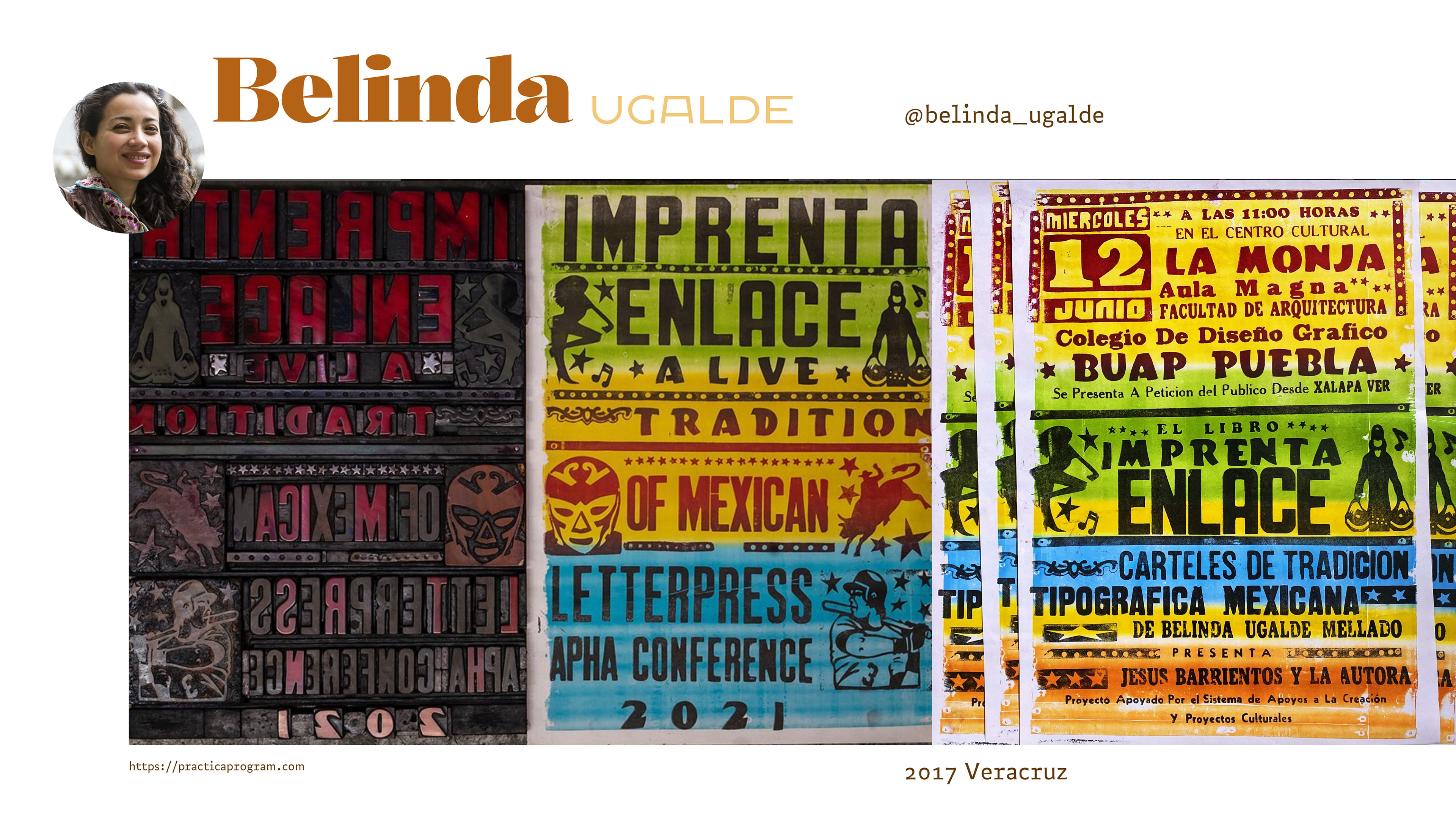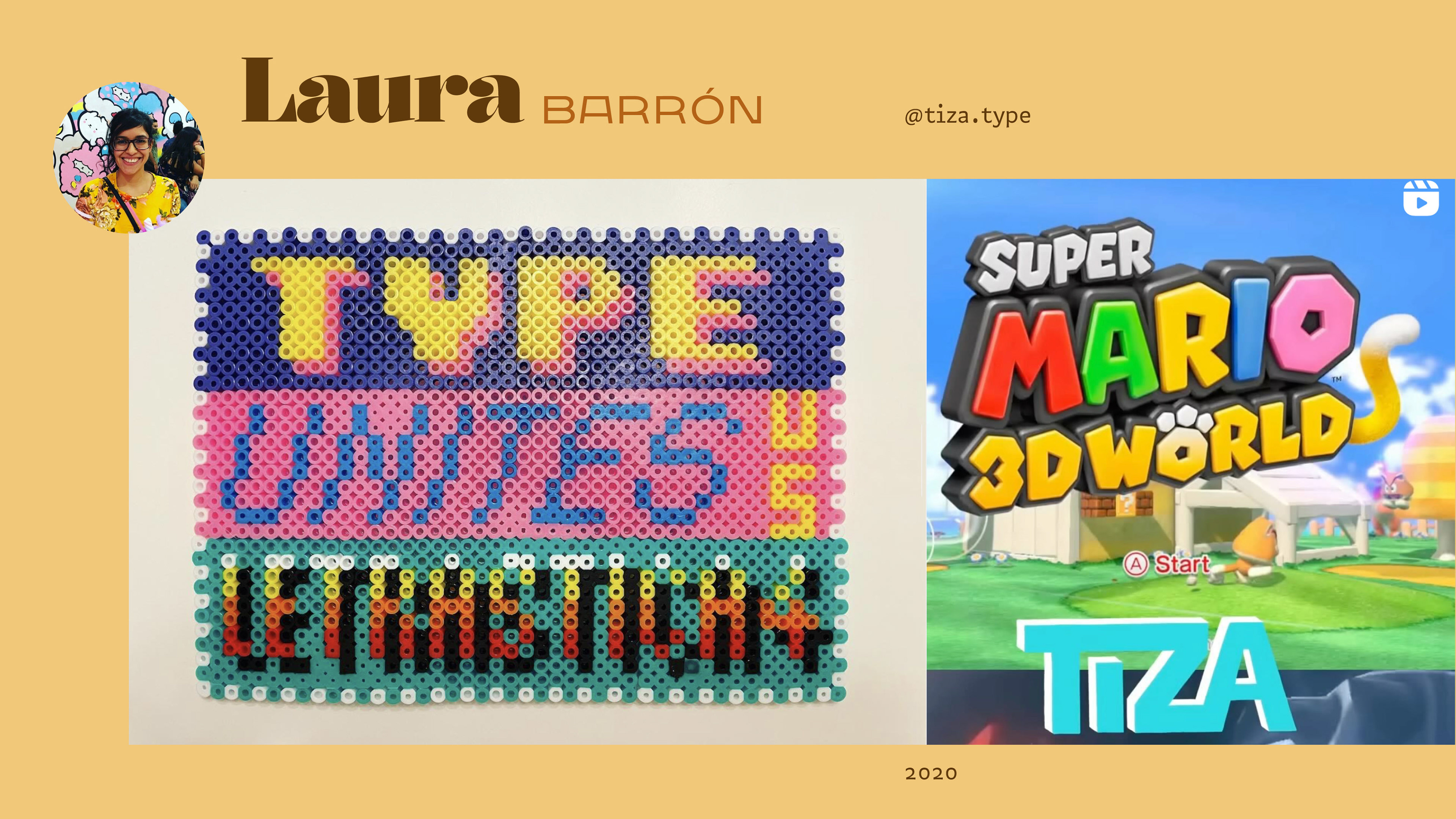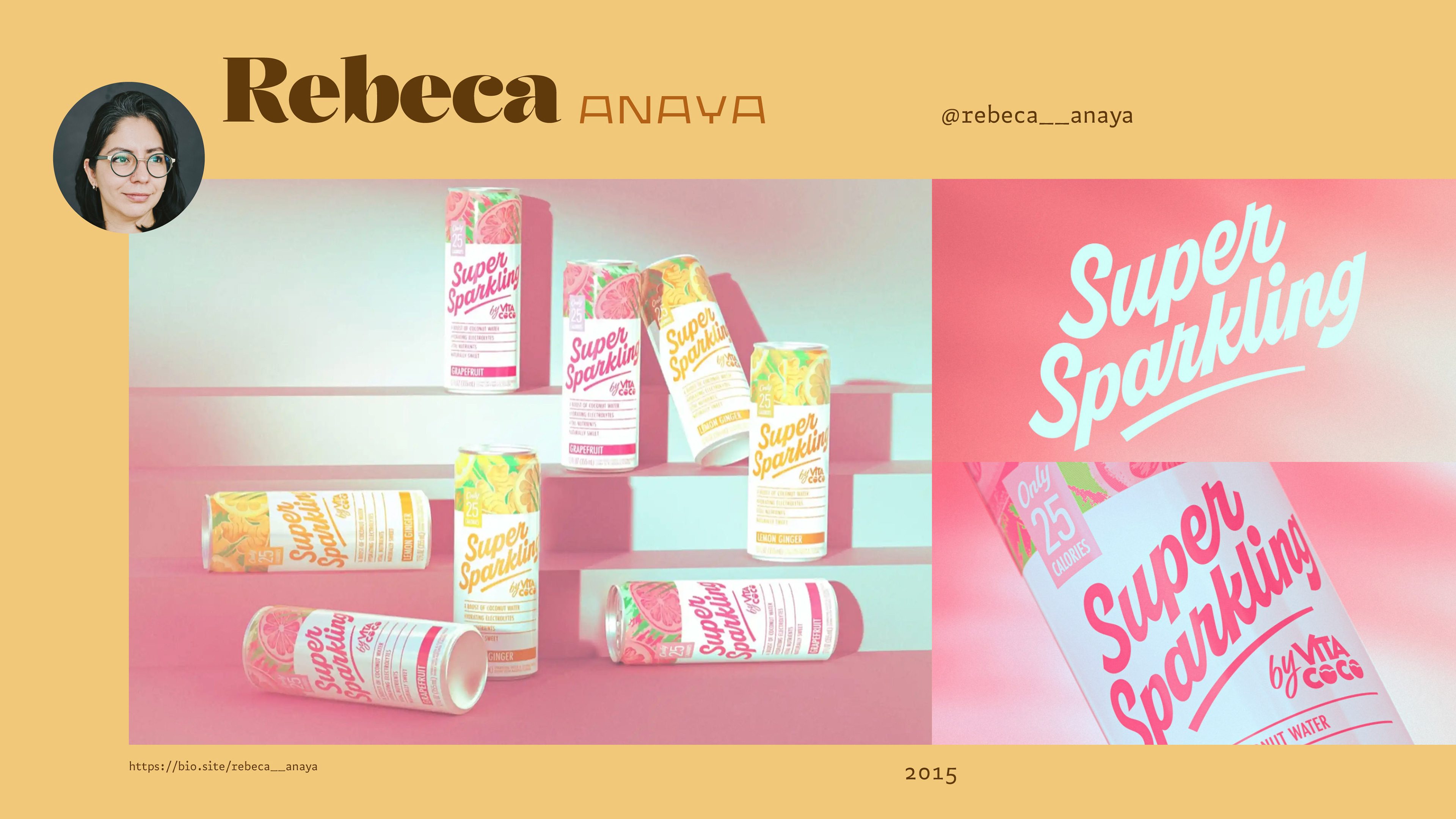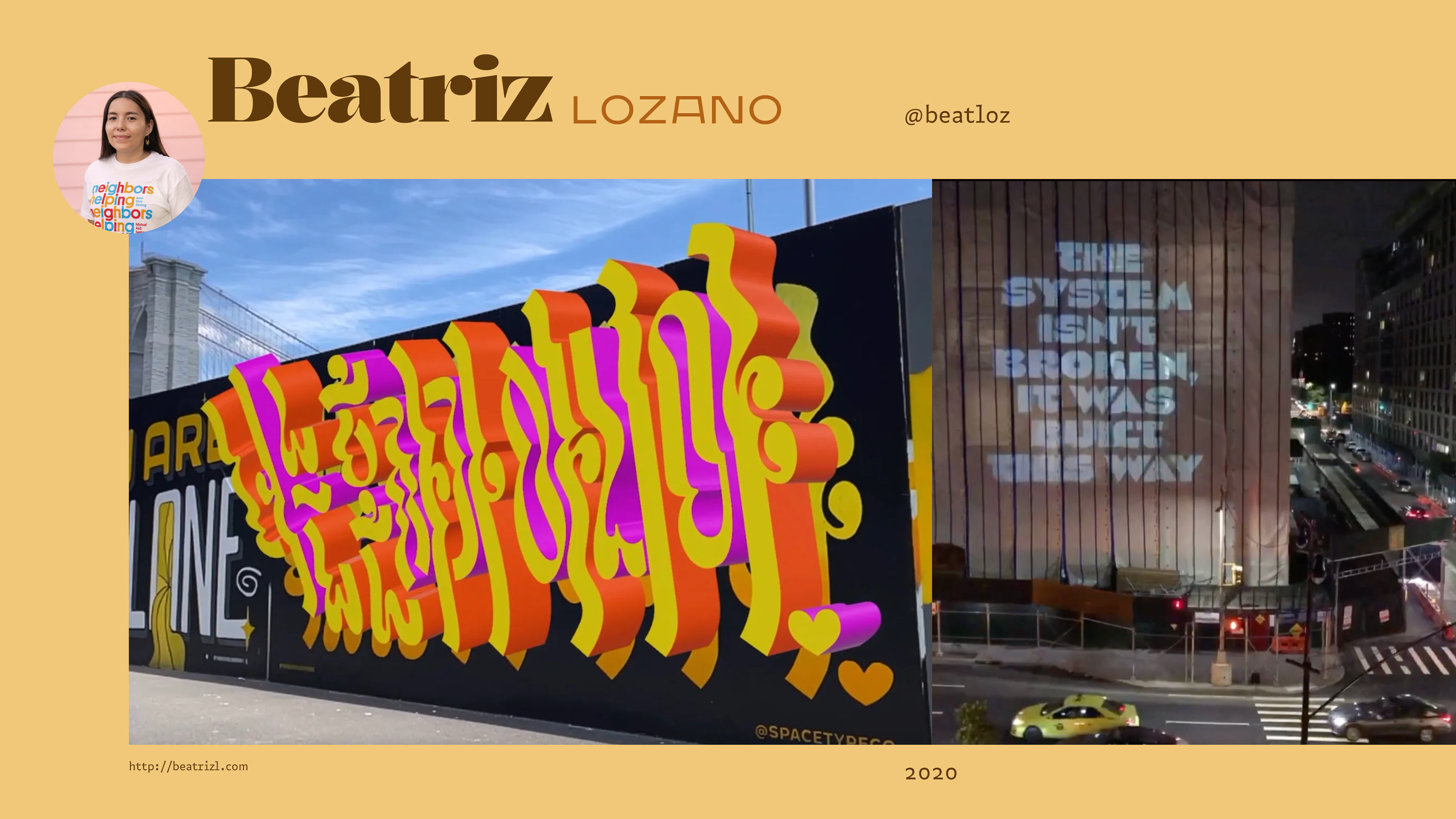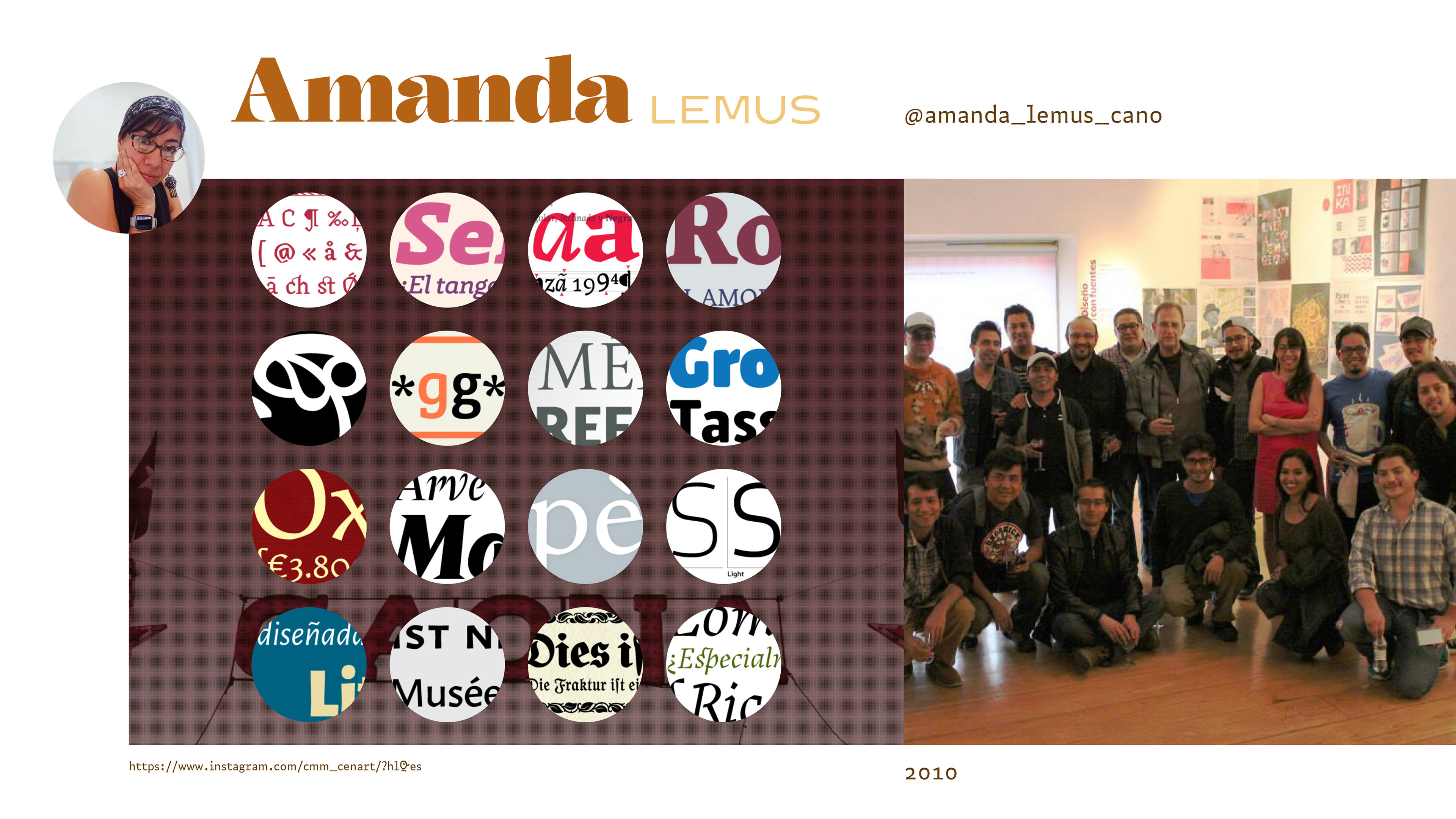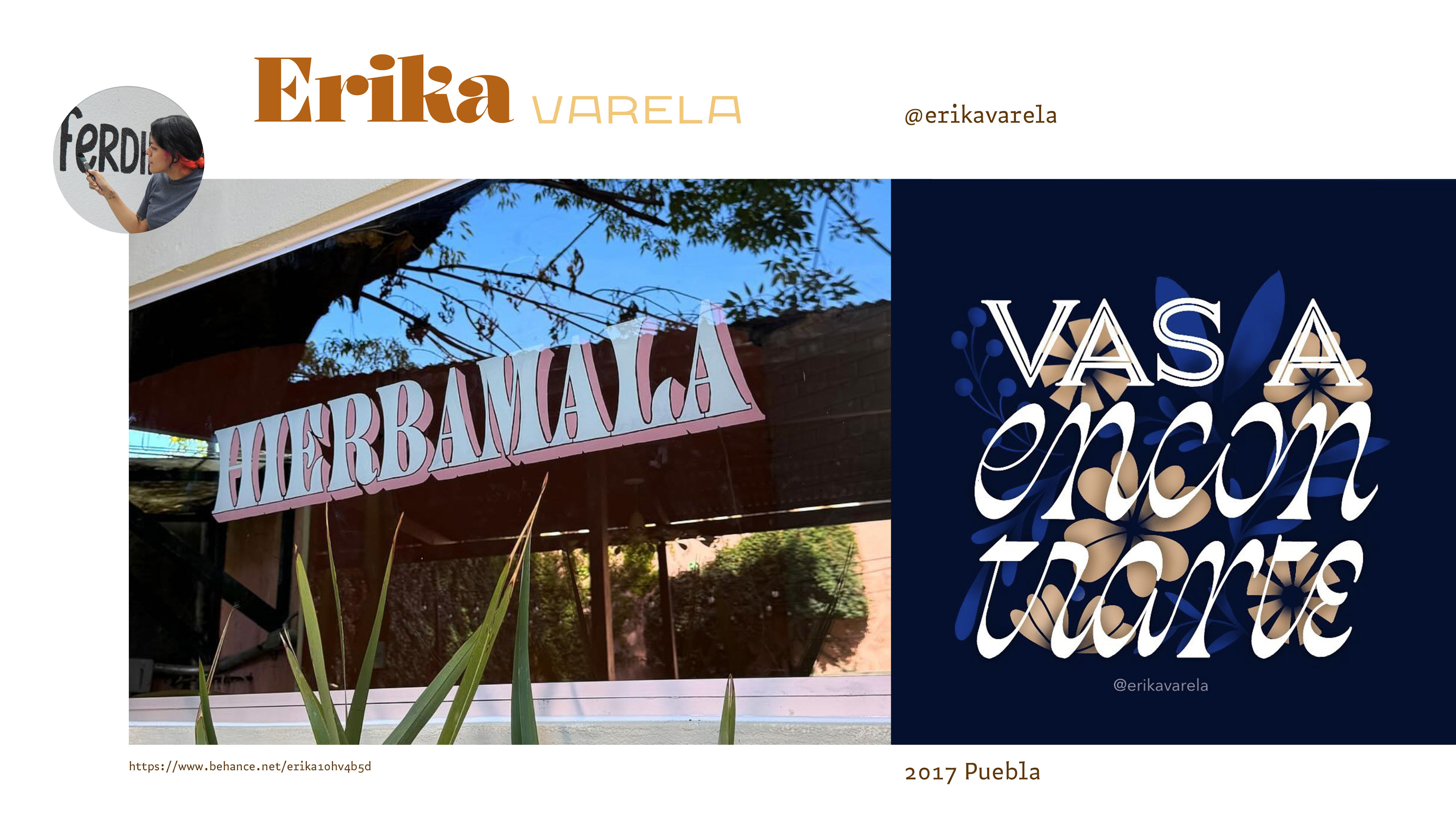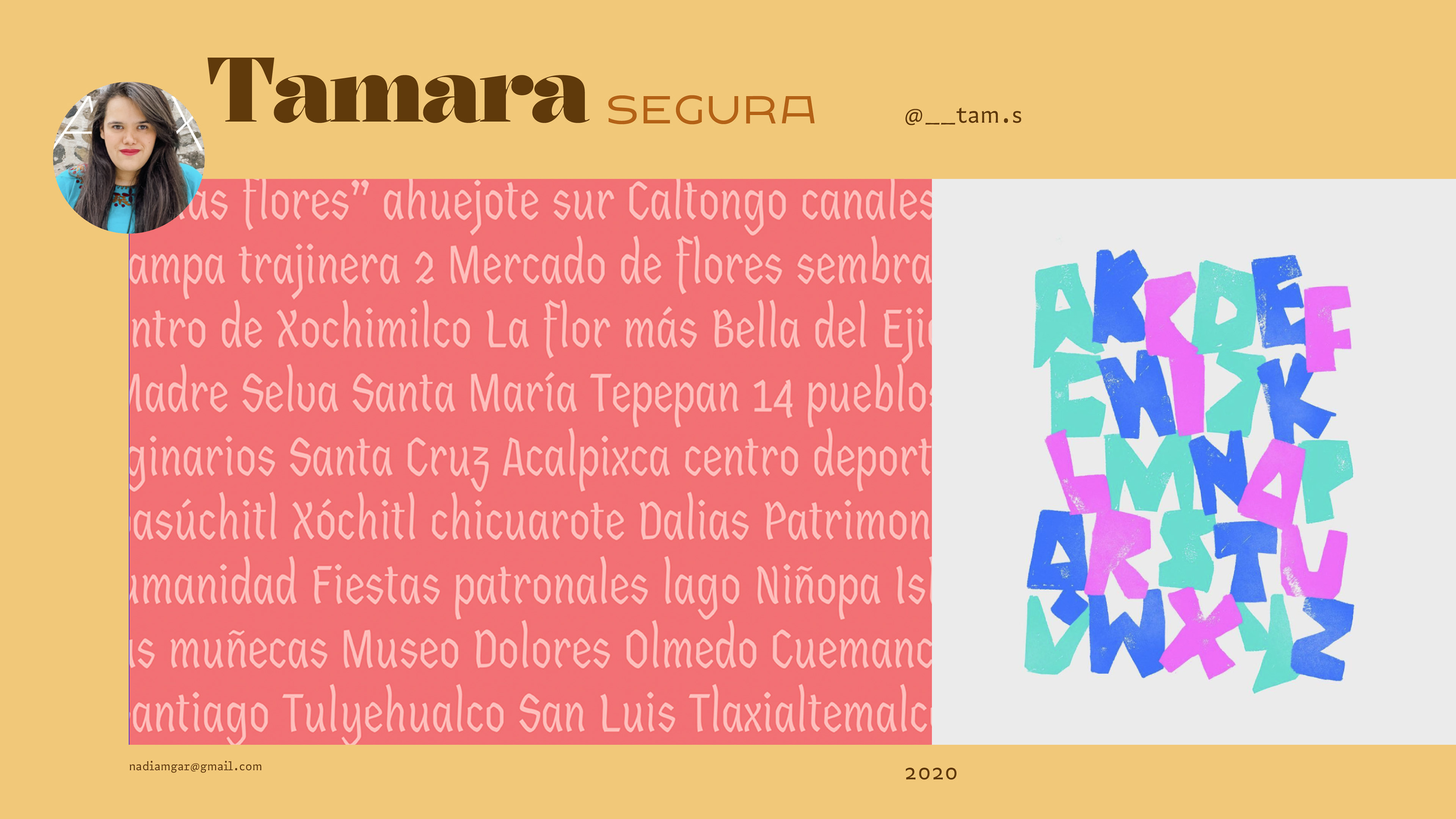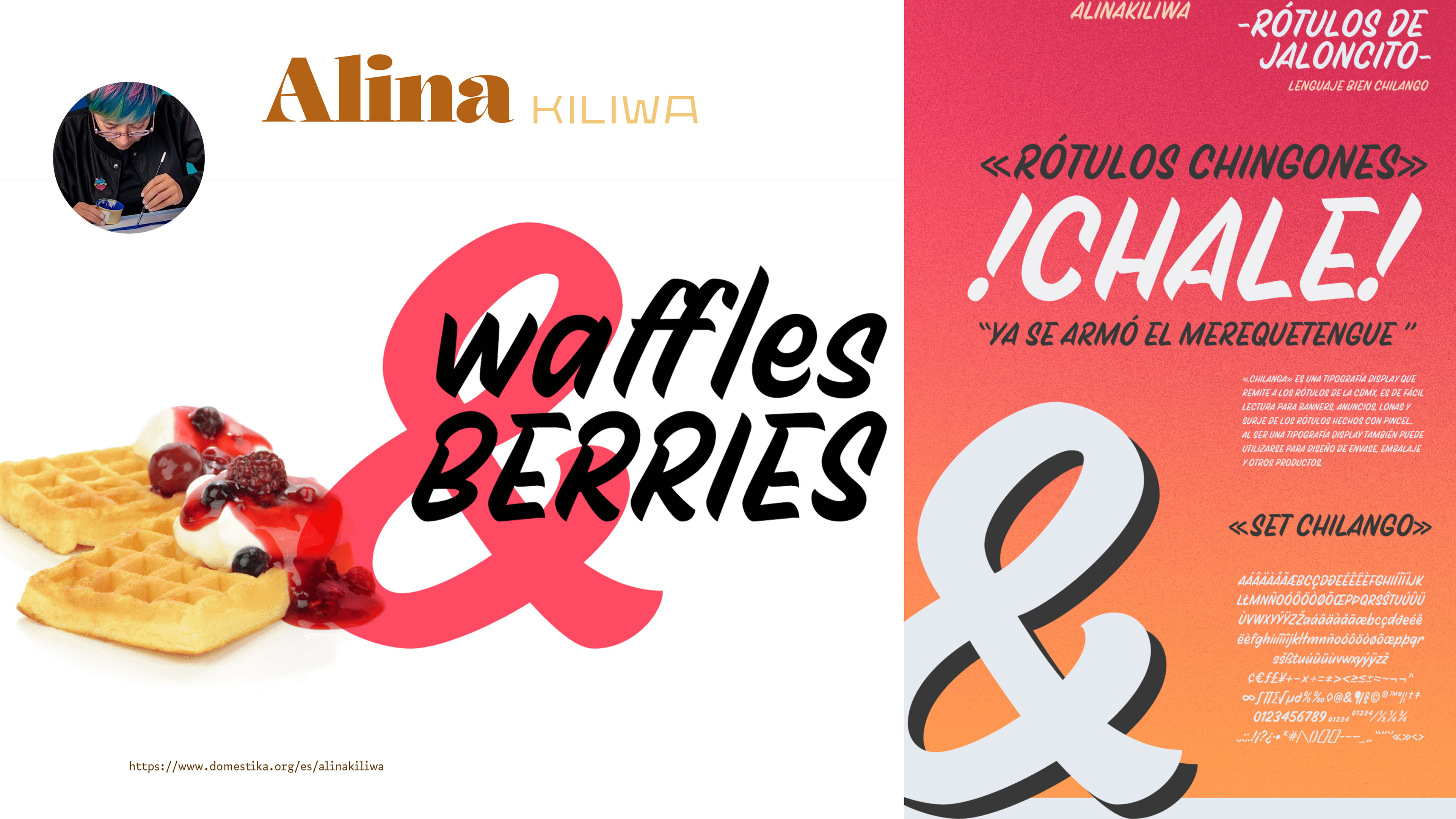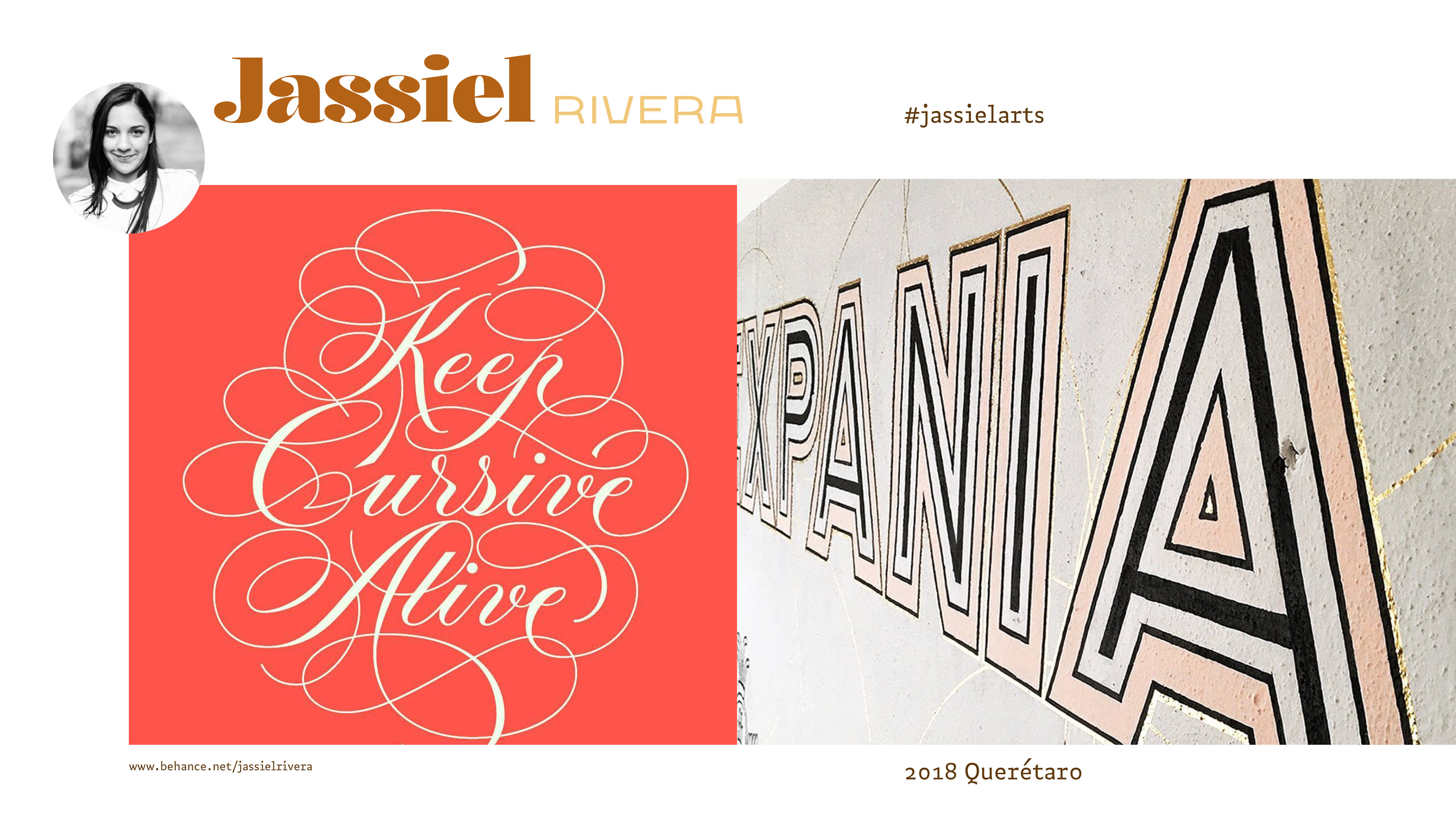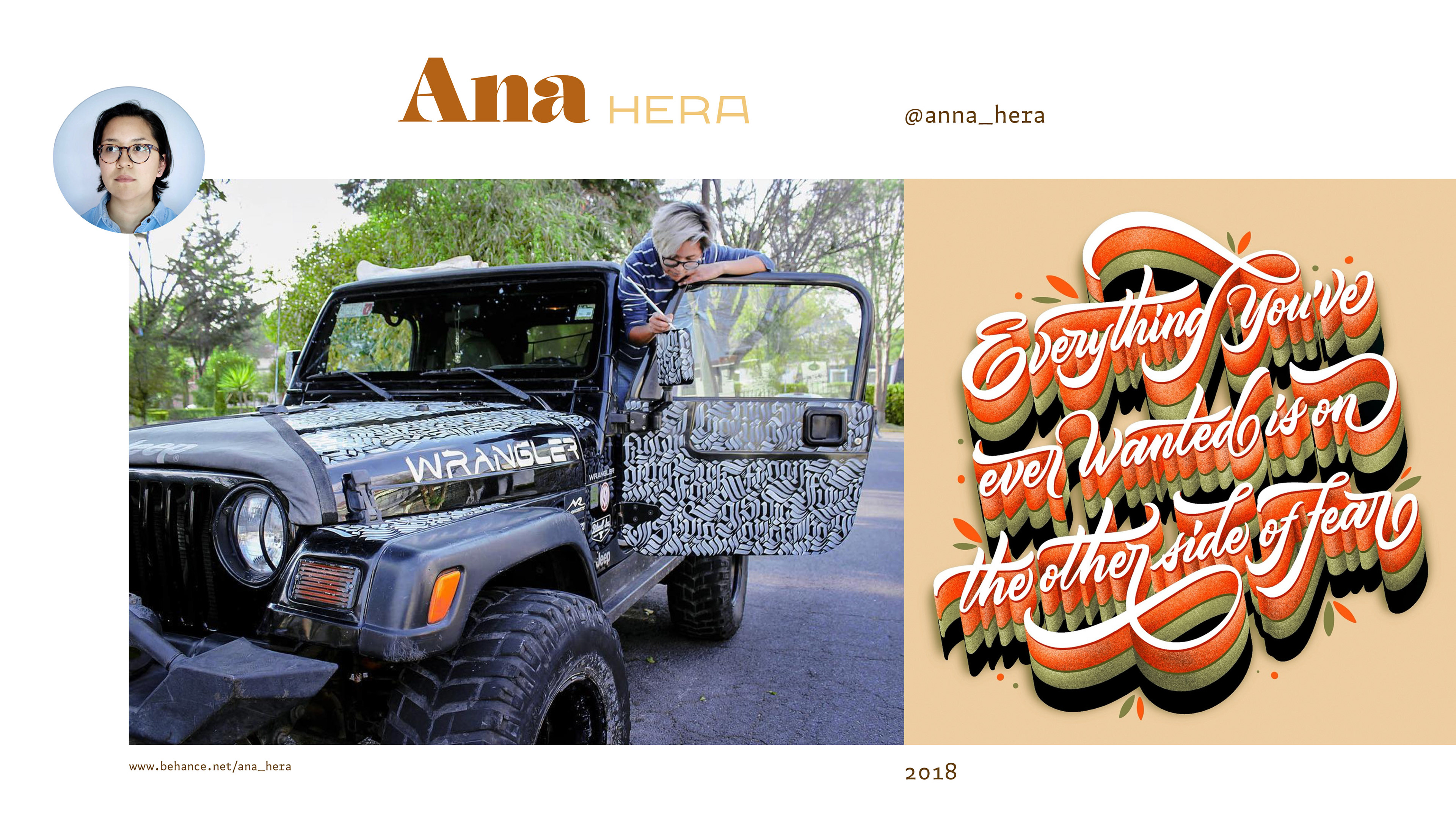
Charla Mujeres tipógrafas contemporáneas en México
Hace unos meses nos invitaron a hablar sobre tipógrafas, y nos dimos a la tarea de realizar una pequeña charla sobre ellas: las mujeres que, en su práctica, se dedican a usar la letra desde varias disciplinas. Creemos firmemente que la letra es versátil y se enriquece con el rótulo, la caligrafía, el letterpress, el lettering y muchos otros instrumentos que, sin lugar a dudas, fortalecen las decisiones dentro de la construcción de un sistema tipográfico y ofrecen un panorama histórico, con la evolución misma de la escritura.
Dentro del territorio tipográfico mexicano podemos encontrar y destacar a grandes diseñadoras de tipografia, rotulistas, calígrafas, letristas y directoras de arte, difusoras del quehacer tipográfico, que desde su trinchera nos han compartido, a través de sus proyectos, a nivel nacional y global, su constante construcción en esta área del diseño tan especializada. Y es que, al observar sus trayectorias, lugares de procedencia, grados de estudio y producción tipográfica, sin lugar a dudas, nos dejan perplejos con sus propuestas de diseño e investigación en cada uno de sus proyectos, los cuales nos emociona compartir, pues no podemos creer que no existan vitrinas digitales que muestren esos rostros, esos nombres y, sobre todo, esos proyectos que sabemos que la gran mayoría de los diseñadores y creadores de tipografía desconocen y que deberían ser referentes para muchos de nosotros.
Esta es una pequeña muestra y recopilación de lo que, a lo largo del tiempo, hemos ido investigando y conociendo sobre estas talentosísimas diseñadoras de letras que han buscado profesionalizarse en el área.